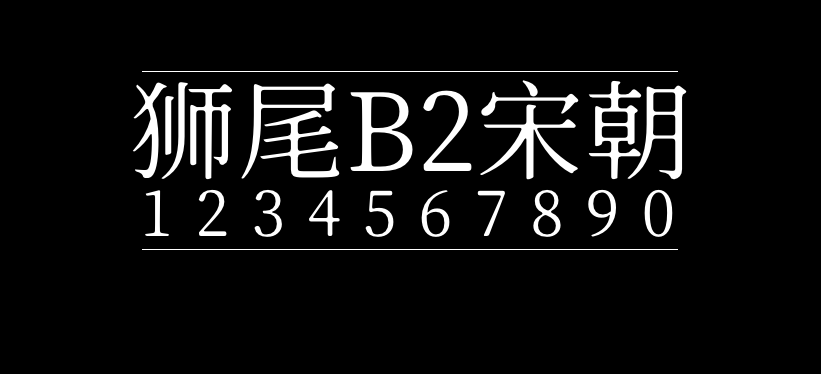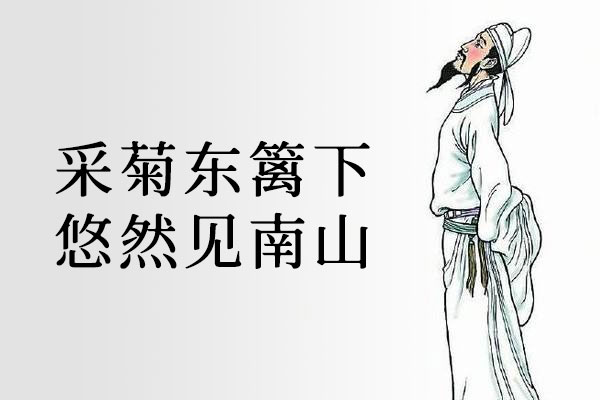
狮尾B2宋朝
狮尾B2宋朝字体(Swei B2 Serif CJKtc)是中国台湾的MAX基于思源宋体创作的一款字体,将转角的三角形通过程序自动转成半圆形改造,看起来好像墨晕或是稍微过曝的效果。支持简体中文、繁体中文、韩文与日文;欢迎大家自由应用、自由优化、自由改作!
该字体有7个字重,由于是基于思源宋体改造,所以字符很全,各位不用担心缺字问题。